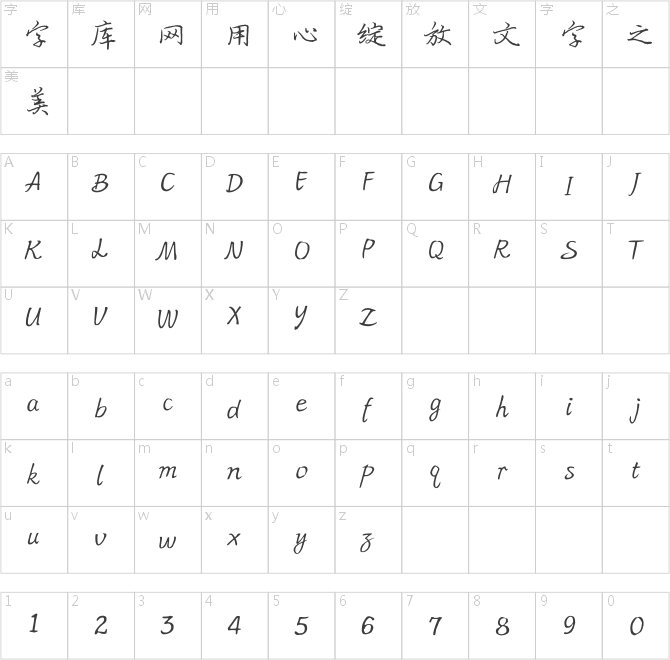
方正字跡-新式古風(fēng)行楷 詳情頁(yè)
作者愛(ài)好書(shū)法并喜歡尊崇古法,但不拘泥于某個(gè)風(fēng)格,對(duì)字的結(jié)構(gòu)有個(gè)人深刻研究。該款字傳承“中庸”思想,不張揚(yáng)做作,繼承古人同時(shí)取法今人審美。
方正字跡-新式古風(fēng)行楷字體字庫(kù)是一款讓人賞心悅目、百看不厭的中文字體,適合各類(lèi)廣告和產(chǎn)品包裝設(shè)計(jì)應(yīng)用,字體大小8.22MB,格式為T(mén)TF字體,上傳用戶是雅銳廣告李玥,作者/版權(quán)方為方正字跡